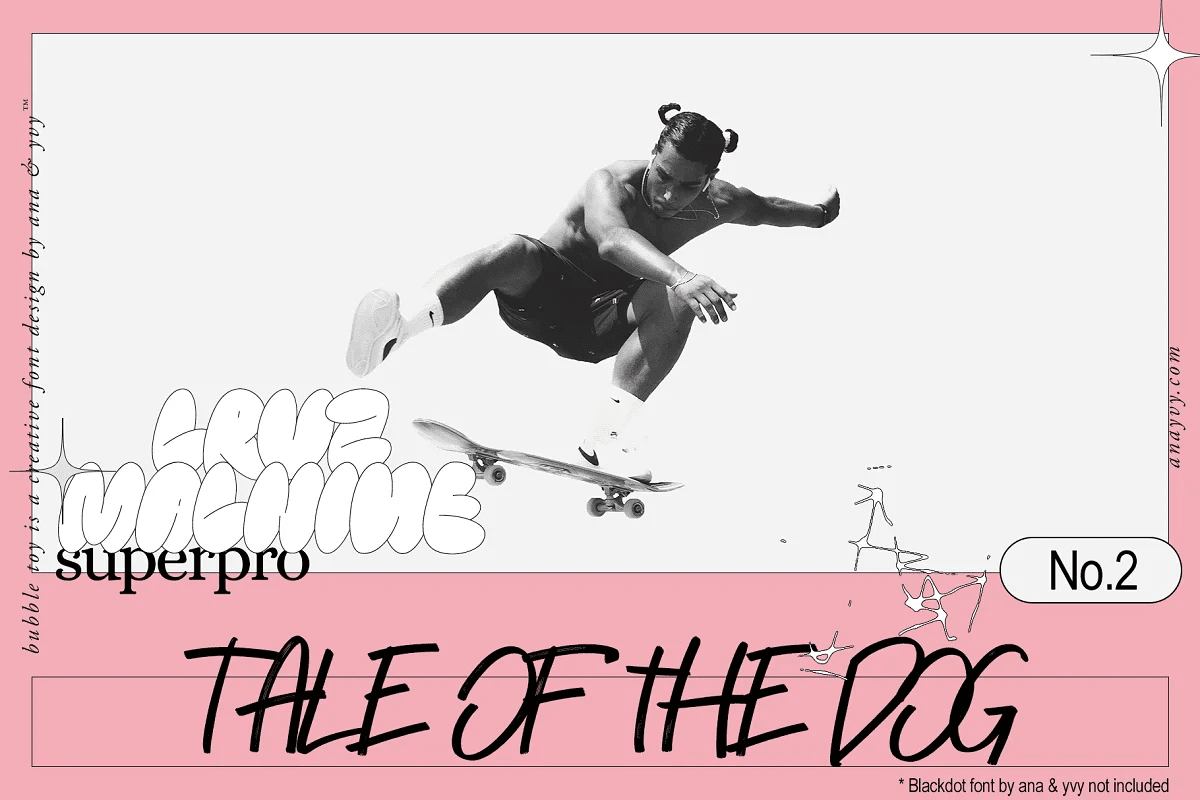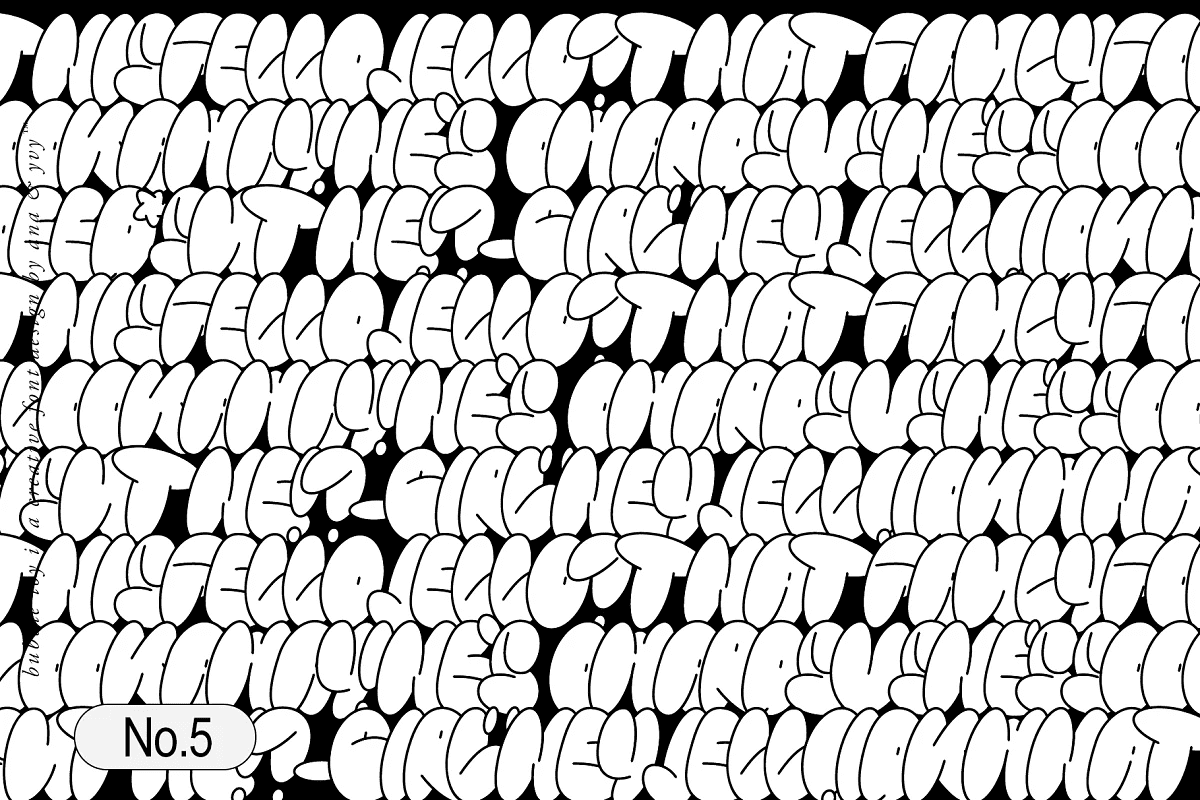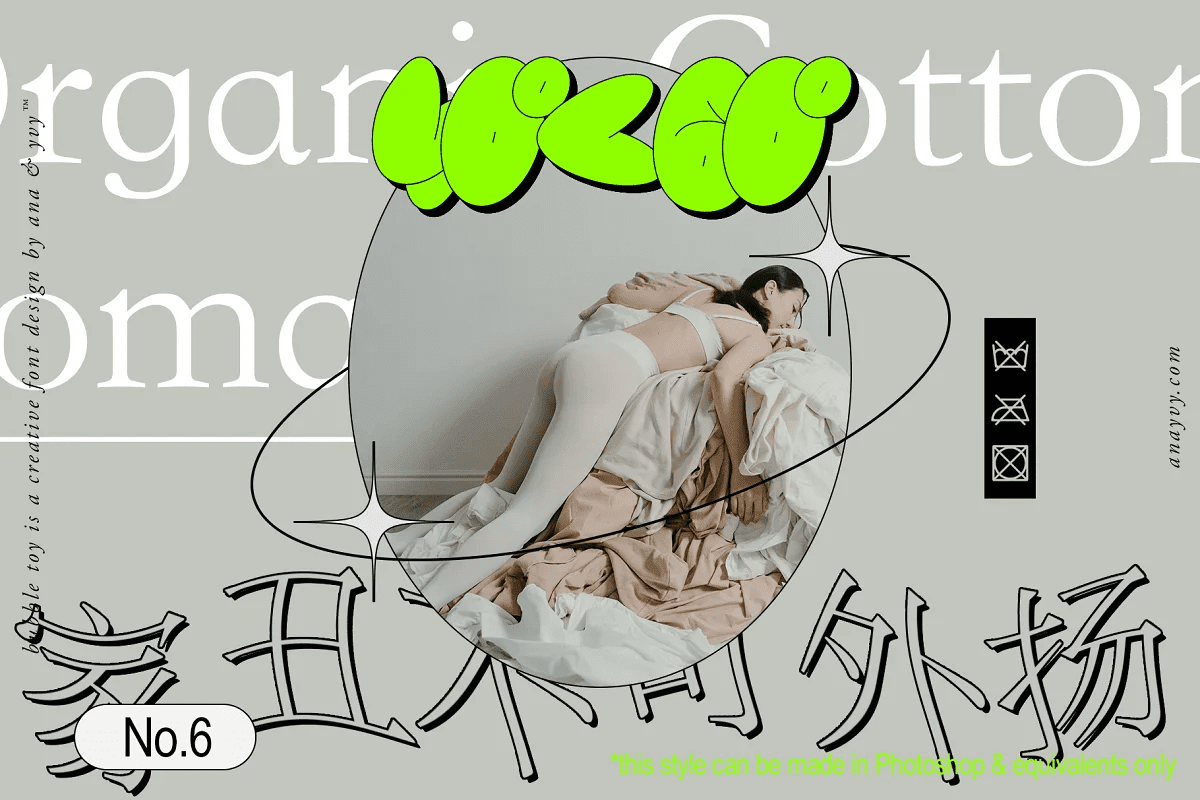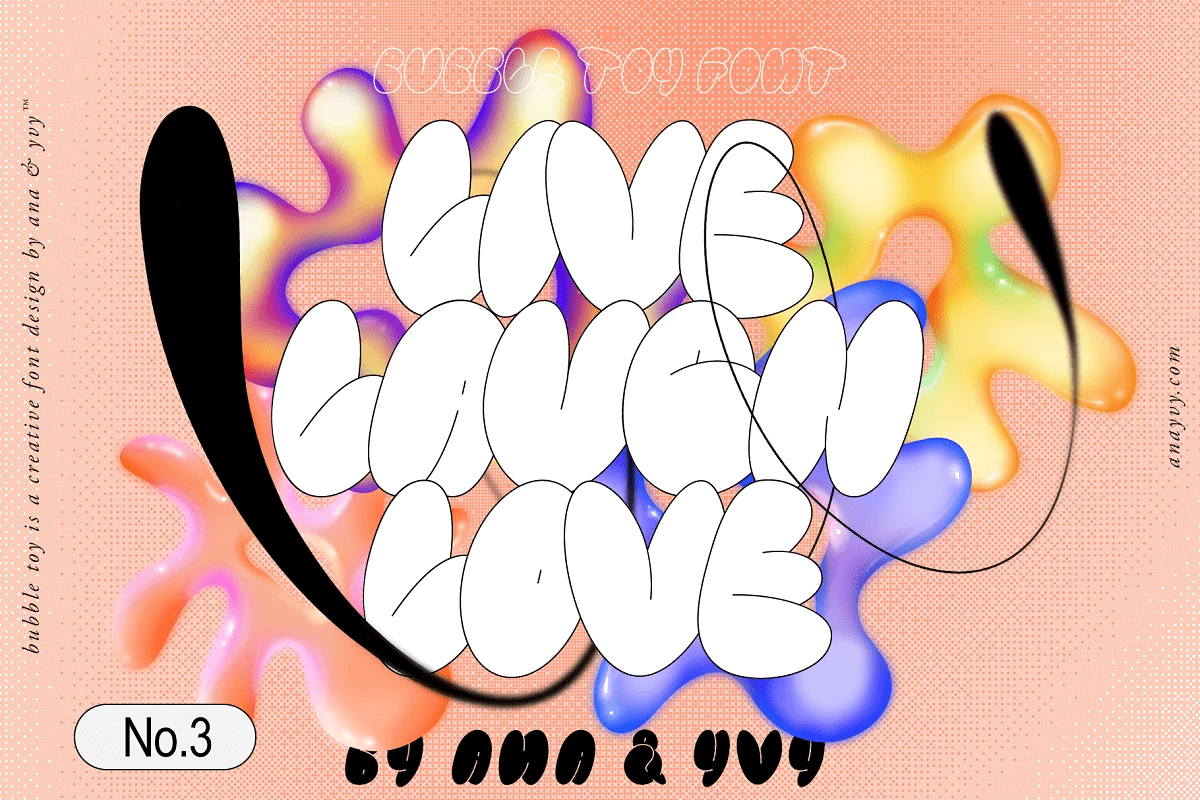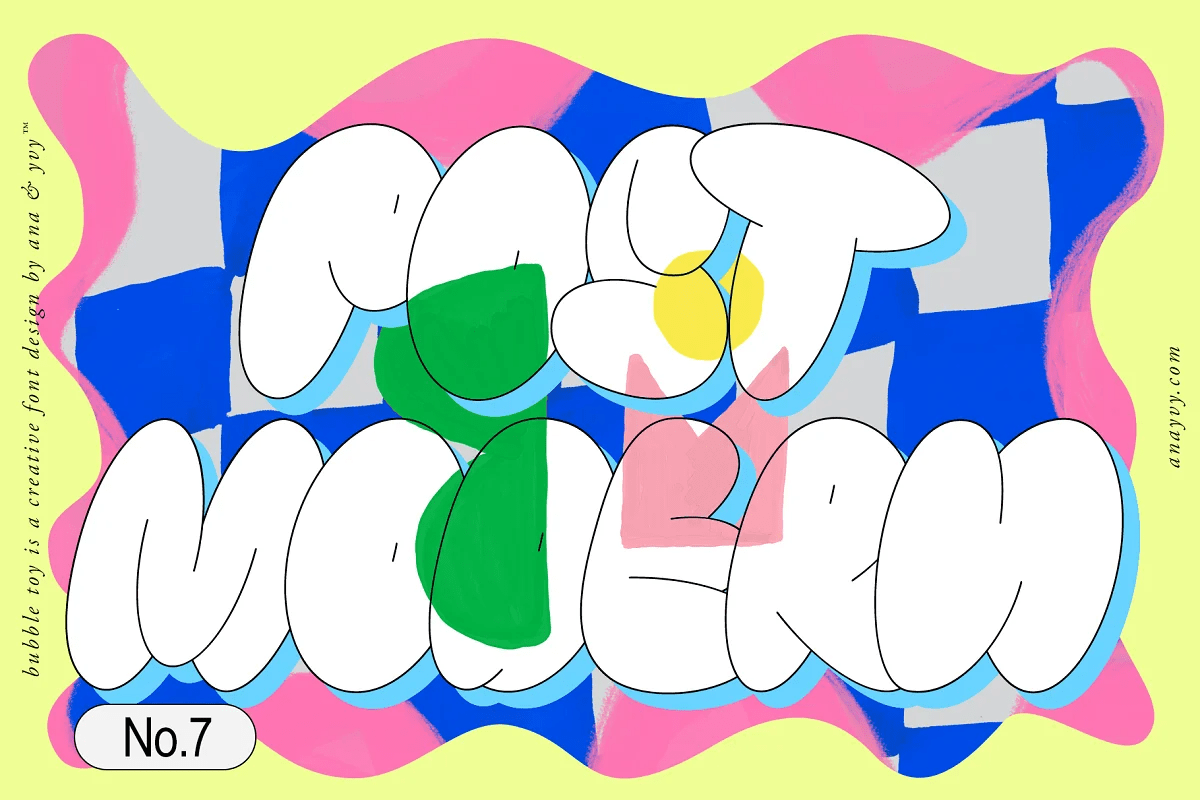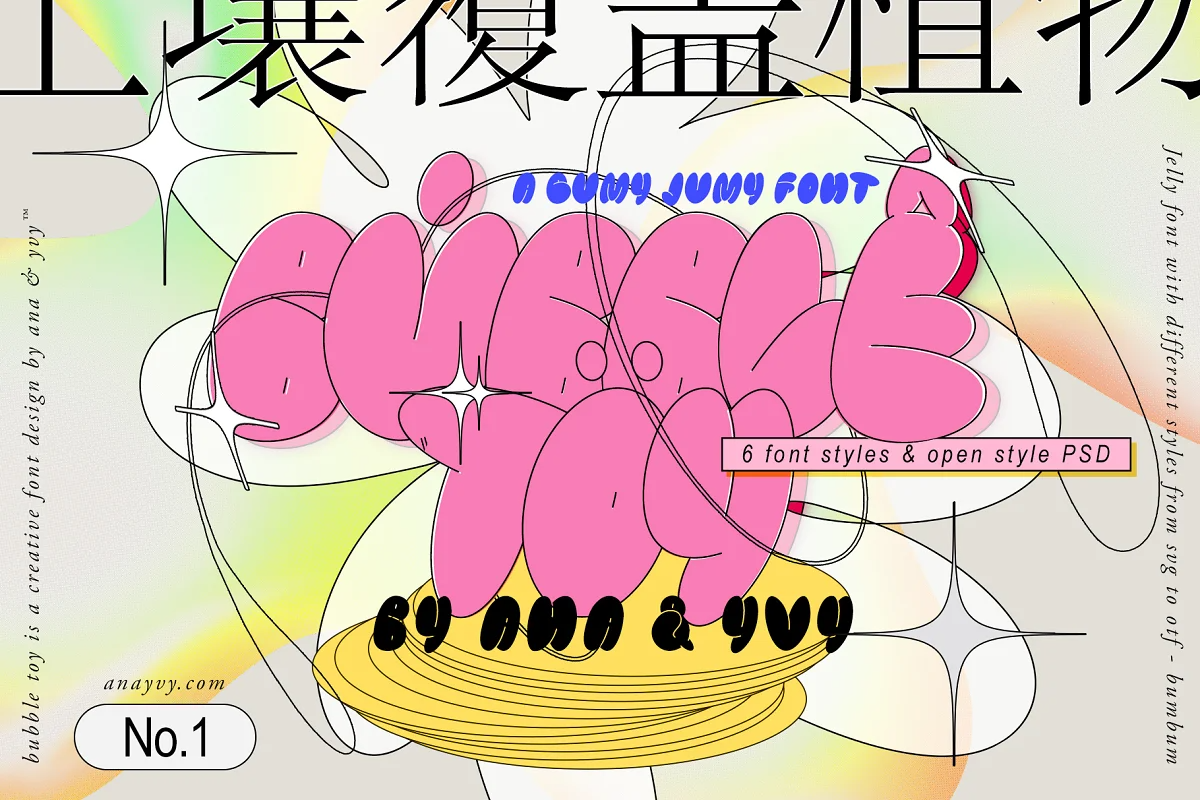
Bubble Toy – bộ phông chữ graffiti lấy cảm hứng từ thập niên 90 và 2000 với 6 kiểu. Phong cách bong bóng thủ công vui nhộn ở chất lượng vector.
CÓ GÌ BÊN TRONG
- trơn với đường cắt phác thảo – màu đen đều đặn
- trơn với đường cắt phác thảo – đen đậm
- chỉ phác thảo – thường xuyên
- chỉ phác thảo – in đậm
- SVG viền đen tô màu trắng – thông thường
- SVG viền đen tô màu trắng – đậm